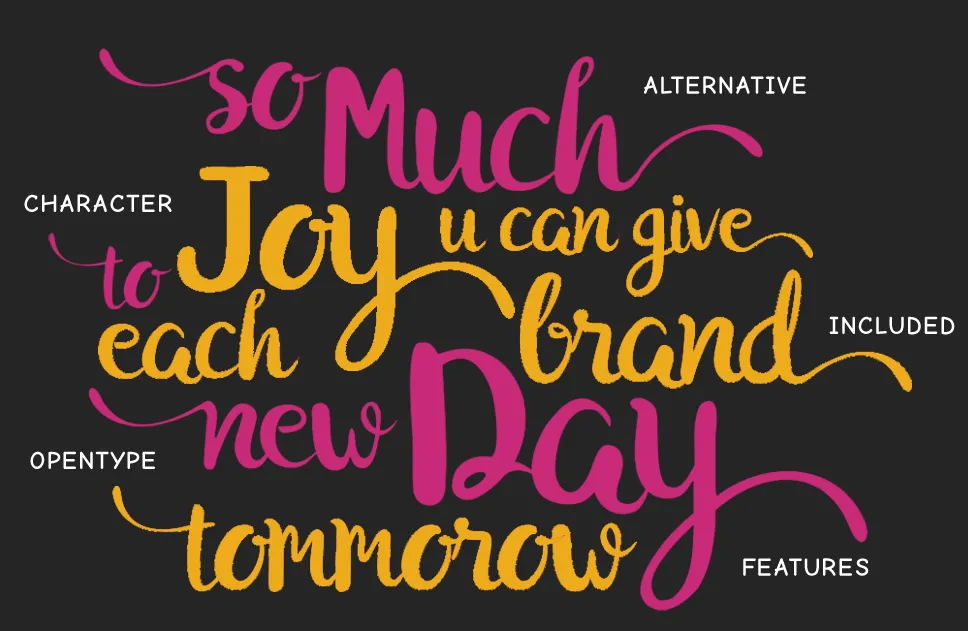
Hayuk Script Font – Fonte Grátis
Hayuk Script Font
A Hayuk Script é uma tipografia de script feita à mão com um estilo único. Esta fonte não apenas é única por sua simplicidade e elegância, mas também pelo seu detalhado toque pessoal que adiciona uma qualidade sofisticada ao design. Suave e firme na mesma medida, ela oferece um conjunto de caracteres perfeito para um leque ampliado de usos: desde logotipos e marcas criativas até cartões de convite e cards de agradecimento, o Hayuk Script complementa qualquer projeto gráfico que você possa estar criando. Sempre elegante e inovadora, ela é perfeita para aqueles designers em busca de uma fonte que se destaca do resto.